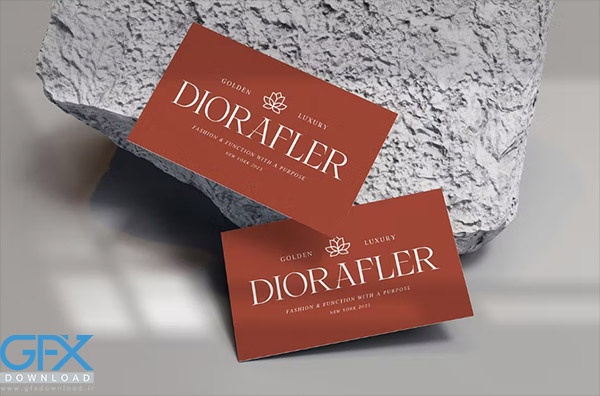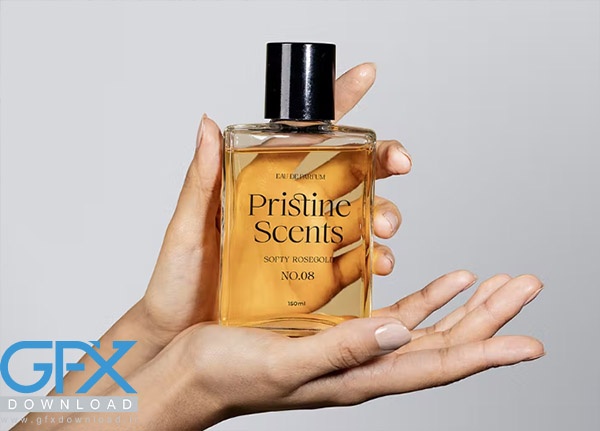
فونت انگلیسی رایگان Glamore
فونت انگلیسی زیبا رایگان Glamore
Glamore یک فونت serif تمیز است که سبک سنتی را در یک زیبایی‌شناسی معاصر ترکیب می‌کند . با ظرافت و راحتی ساخته می‌شود و به راحتی با مجموعه بزرگی از پروژه‌ها هماهنگ می‌شود . از این فونت انگلیسی رایگان Glamore برای رسیدن به یک ظاهر زیبا , با در عین حال دقیق و متنوع استفاده کنید . شامل : حروف بزرگ - کوچک - نماد نقطه‌گذاری, نقطه‌گذاری , پشتیبانی چند زبانه - چند زبانه. پرونده شامل : ( OTF , TTF , WOFF , WOFF2 ) می باشد.